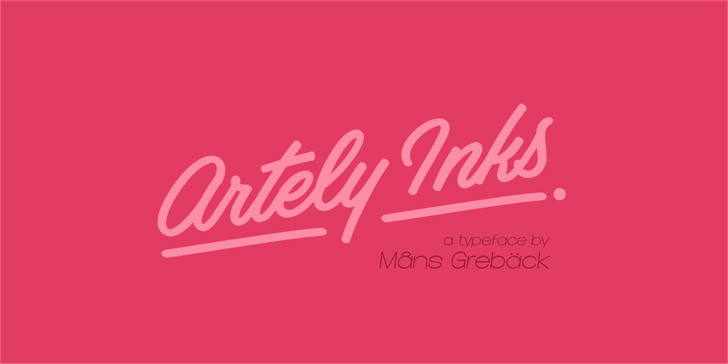
A fonte “Artely Inks” é uma elegante seleção para designers que buscam um tom mais casual e autêntico em seus projetos. Ela foi criada pelo designer Hamilton, oferecendo linhas suaves e personalizadas perfeitas para texturas manuscritas. Seja você criando cartazes de moda com um estilo retro ou elaborando capas de livros com nuances vibrantes, a “Artely Inks” é uma escolha excepcionalmente versátil. A qualidade de acabamento desta fonte é tão alta quanto sua versatilidade, tornando-a um investimento seguro para projetos comerciais. Para adquirir uma licença comercial, visite o site oficial do designer: http://www.mansgreback.com/artely-inks.